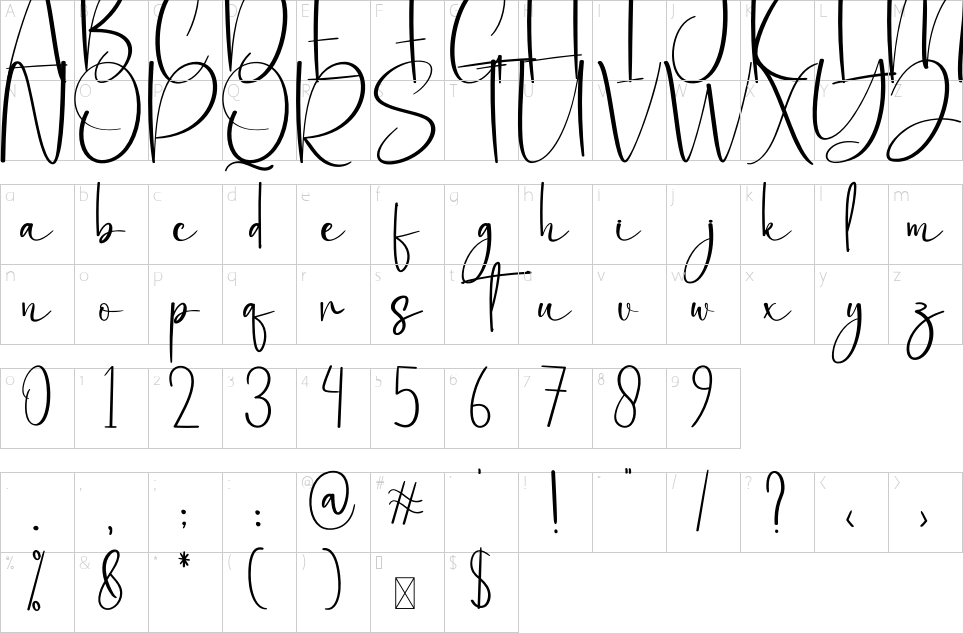
Autography é uma fonte moderna e elegante criada por scratchones, disponível gratuitamente tanto para Windows quanto para Mac. Esta fonte foi projetada para dar um toque único a qualquer projeto de escrita digital. Com linhas leves e uma disposição agradável, Autography é perfeita para usar em design de sites, materiais de marketing, publicações online e até mesmo em design gráfico. Ela ajuda a destacar o texto de maneira atraente sem comprometer a legibilidade. Com seu download já sendo uma experiência muito comum, Autography font já foi instalada por 421 usuários, evidenciando seu valor para designers e criativos. Instale-a hoje e experimente como essa font pode moldar e enriquecer seu próximo projeto.